「MdN2015年7月号」で大好評を博した、「絶対フォント感を身につける。」特集。
10月6日(木)発売の「MdN2016年11月号」にて、前回より内容をパワーアップした「絶対フォント感を身につける。2」が特集されています。
絶対フォント感とは
以前、『ゲームアプリで「絶対フォント感」を鍛える』という記事で、気軽に“絶対フォント感”を鍛えるゲームをご紹介しました。
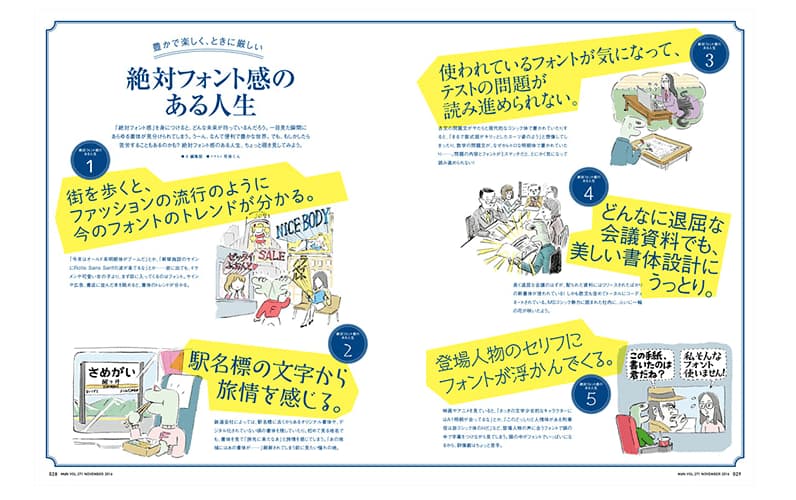
絶対フォント感とは、目にした書体を瞬時に認識し見分ける能力のこと。
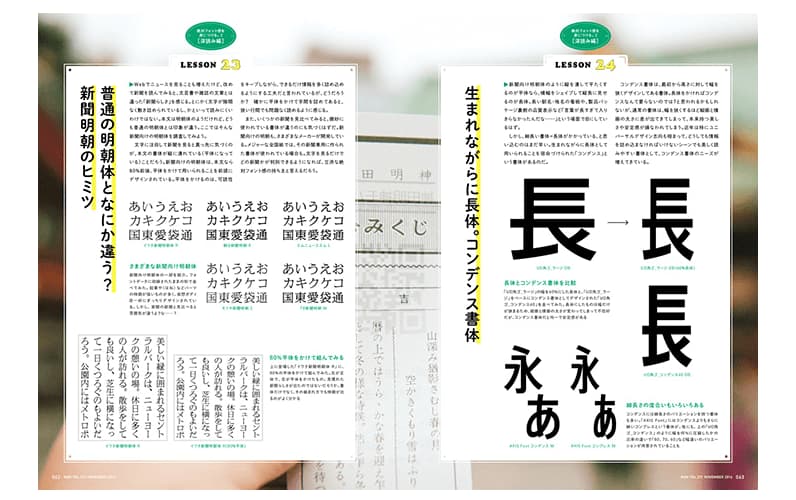
絶対フォント感を極めると、街を歩いているだけで広告や看板などから今の書体のトレンドがわかったり、新聞の文字を見るだけで新聞名を判断することも可能なのだそうです。
充実の内容
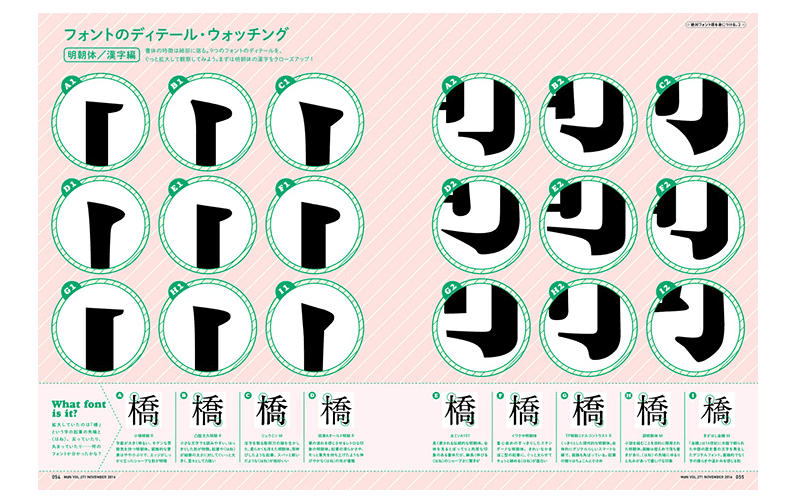
今号の特集では、フォントと書体の基礎を学ぶ「基礎知識編」、実際に見分けるポイントを押さえる「実践編」、ジャンル別に少し踏み込んだ内容の「深読み編」に分け、全26もの“レッスン”を通して、絶対フォント感を身につけるための知識やポイントを紹介しています。
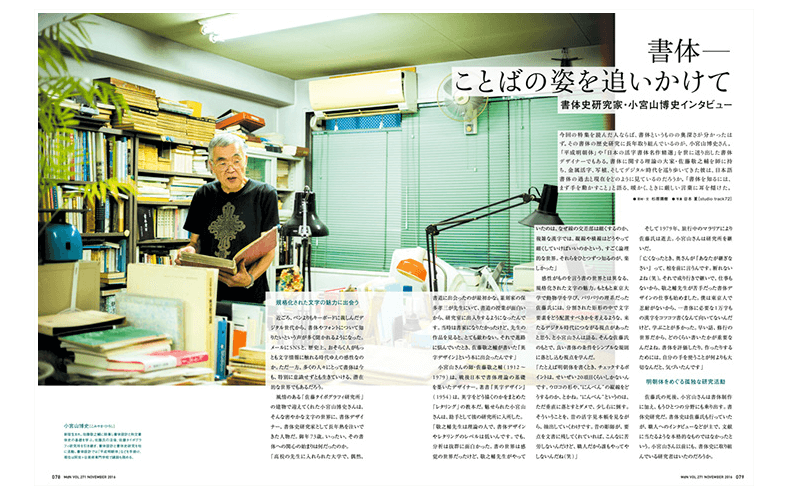
引用元:MdN 公式サイト書体デザイナーであり書体史研究家である小宮山 博史さんへのインタビュー記事では、日本語書体の過去と現在についての興味深いお話が、書籍や装丁の中から写真植字(写植)時代に生まれた名書体を探し、「文字の食卓」の作者である正木 香子さんがその魅力について語るという企画など、読みものも大充実。
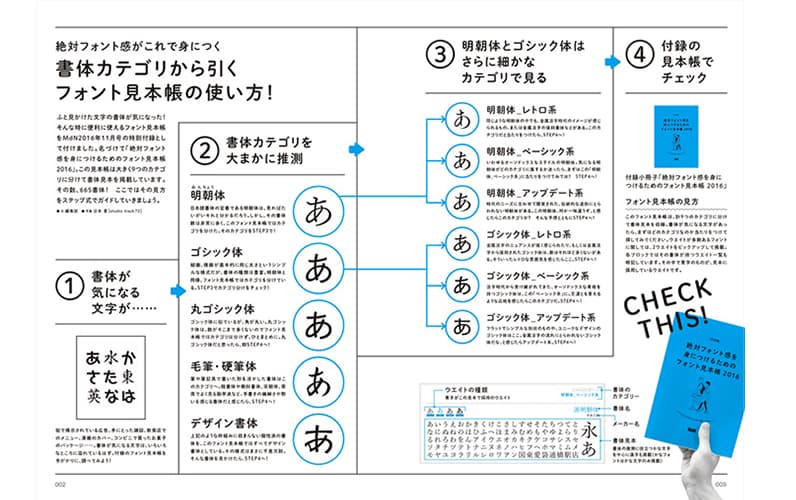
駅にあるさまざまな文字の楽しみ方をレクチャーするページや、665書体を収録したフォント見本帳が付録に用意されているなど、絶対フォント感だけでなく、身近な書体を新たな視点で楽しむ方法が身につく1冊となっています。
書体好きな人はもちろんですが、書体に苦手意識がある人にこそ得られるものが多いかもしれません。